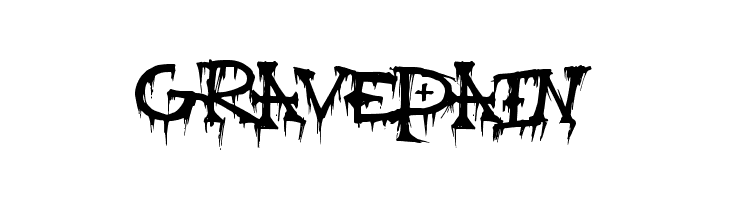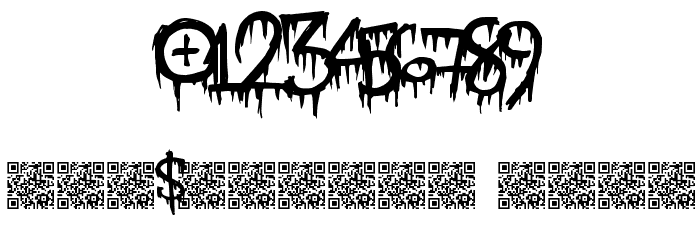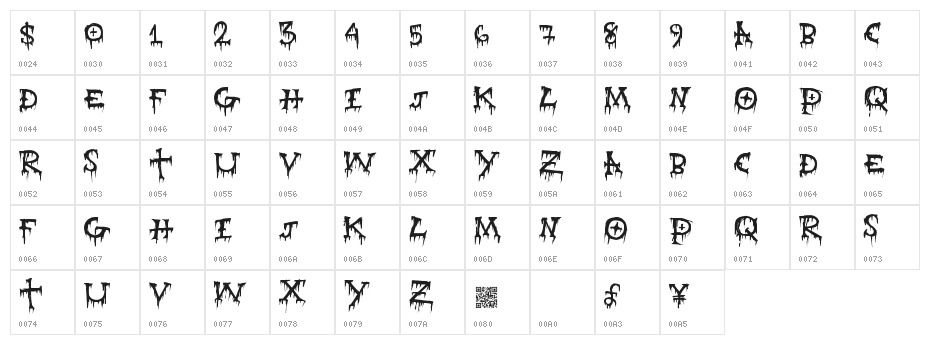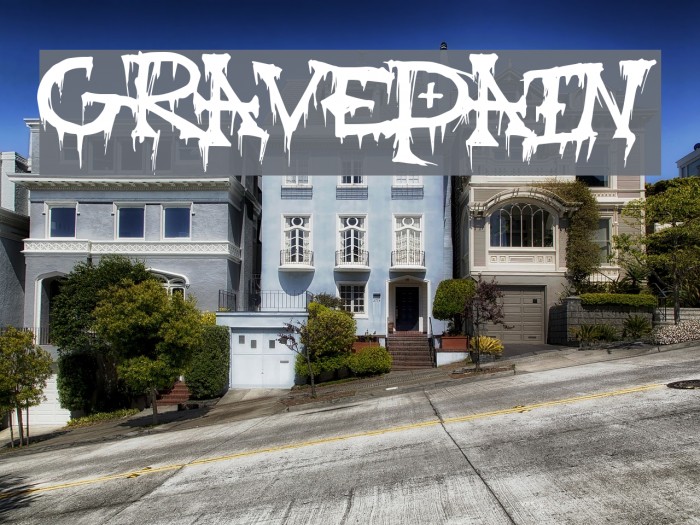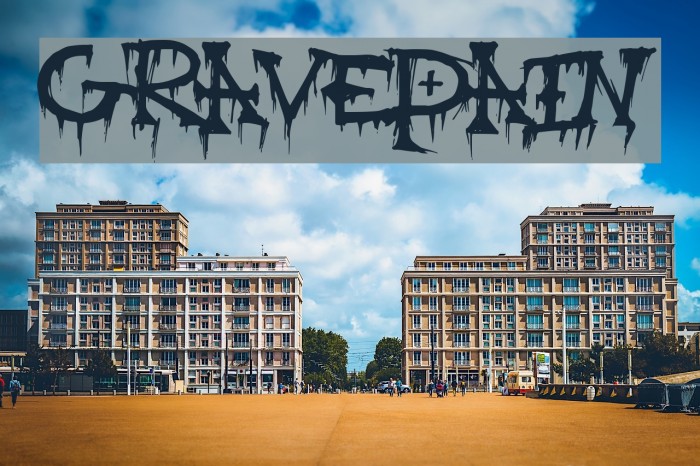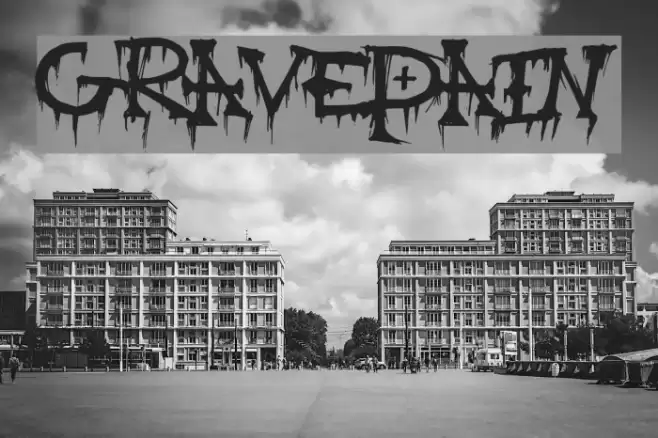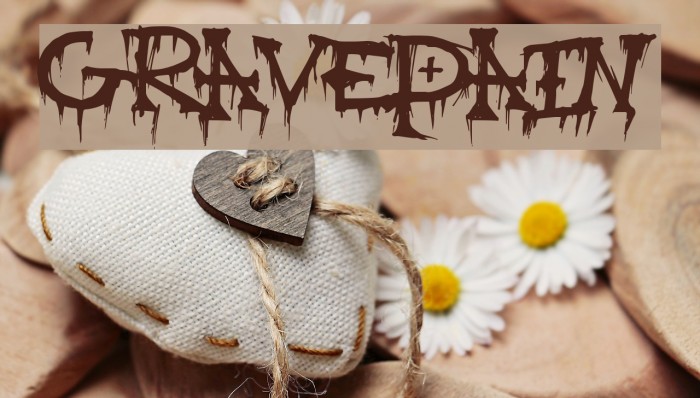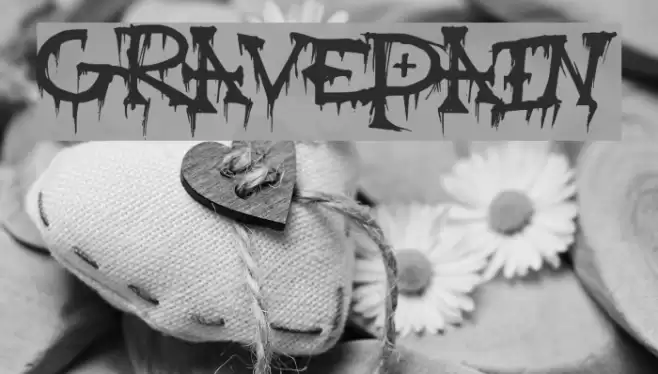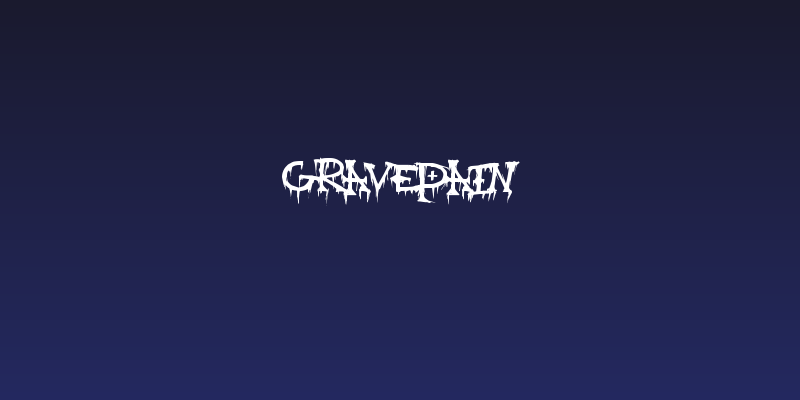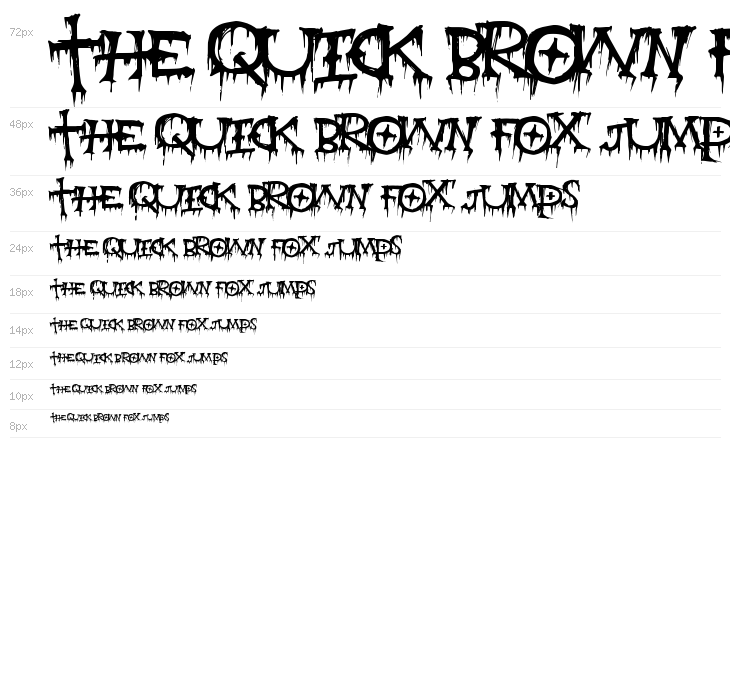
GravePain Font
| Estilo geral | Gothic, Horror, Decorative |
| Caso de uso | Headlines, Posters, Themed Events |
| Projetos propostos | Ideal for Halloween-themed designs, horror movie posters, haunted house flyers, and gothic event invitations. |